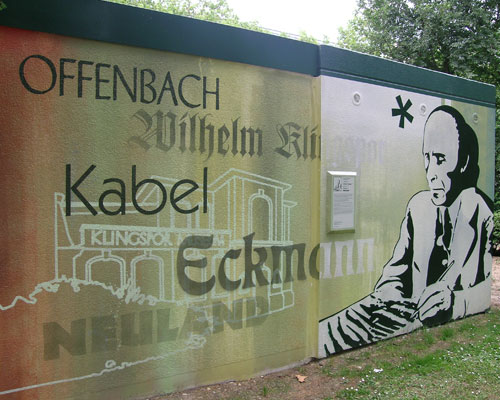
Das Stromverteilungshäusschen der EVO im Büsingpark in Offenbach ist seit einiger Zeit in neuem Gewand zu bewundern. Neben Goethe und Sophie La Roche gibt es je eine Wand über Klingspor und Senefelder. Das Graffiti wurde von artmos4 aus Offenbach umgesetzt.
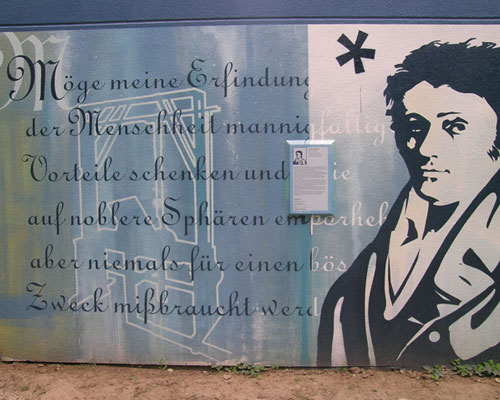
Lediglich die Infotafeln sind mikrotypografisch nicht so gelungen, sondern scheinen ohne tiefgehende Sorgfalt aus Word entlaufen zu sein.
Der Mensch in dem oberen Bild ist Dr. Karl Klingspor, oder? Er sieht wie Dr. Frankenstein aus…
Ich habe diese Wände noch nicht gesehen, aber ich finde es sehr schön, dass es sie gibt. Schade, dass die Infotafeln nicht in einer von die lesbarere Offenbachschriften gesetzt waren.
Heute Abend gehe ich zu eine Ausstellungseröffnung im Klingspor-Museum. Ich werde die Wände danach näher anschauen.
Awesome! Pity they used the ITC version of Kabel.
Yes… that version isn’t even really deserving of the name…